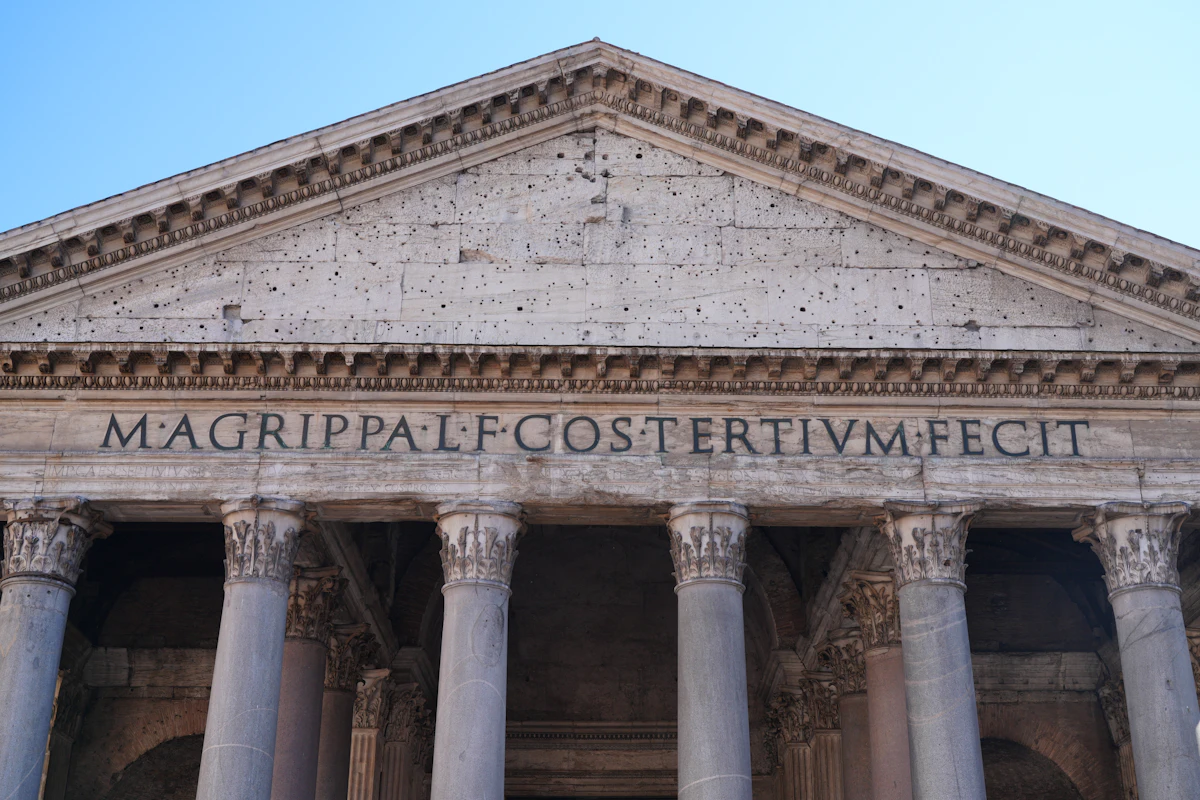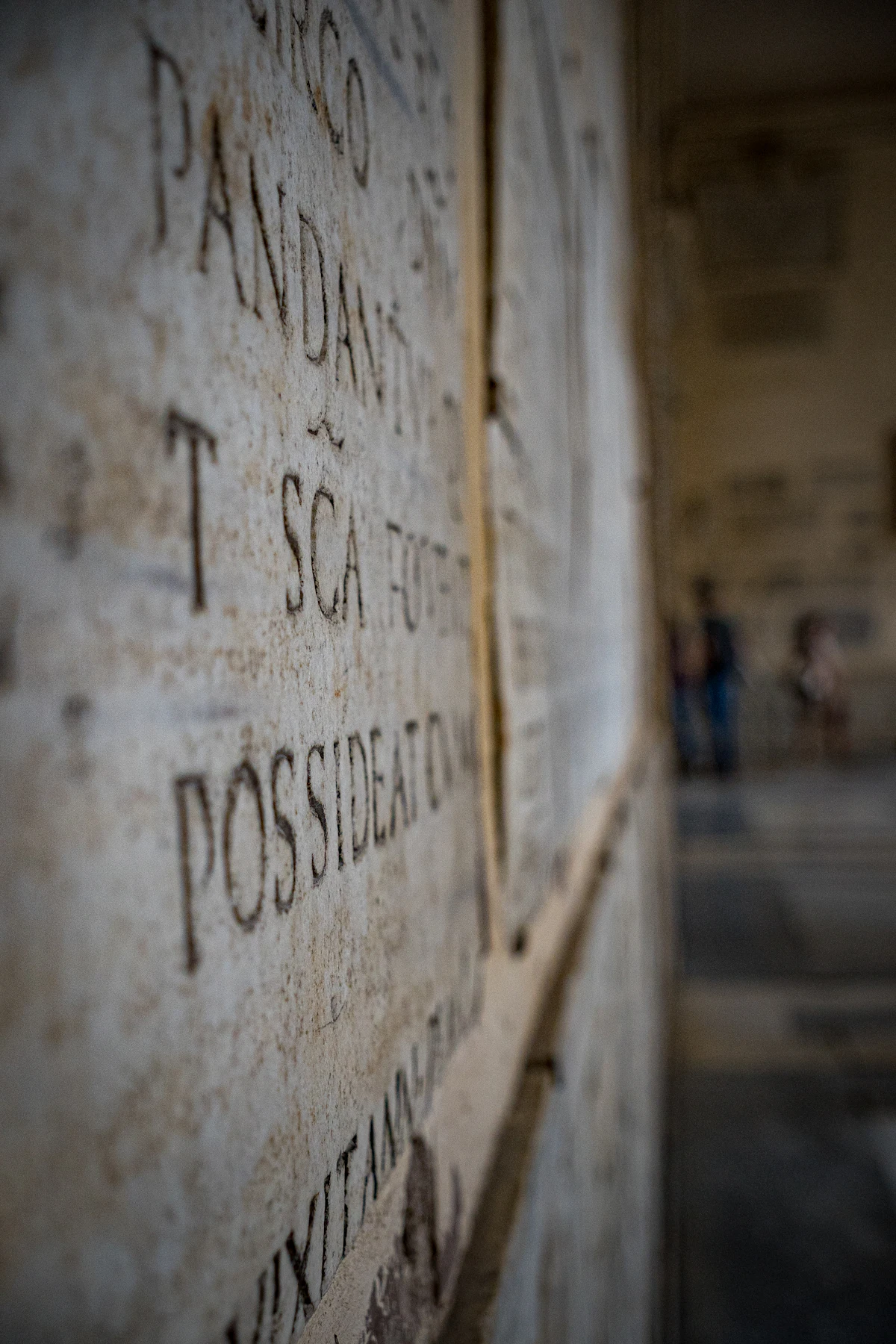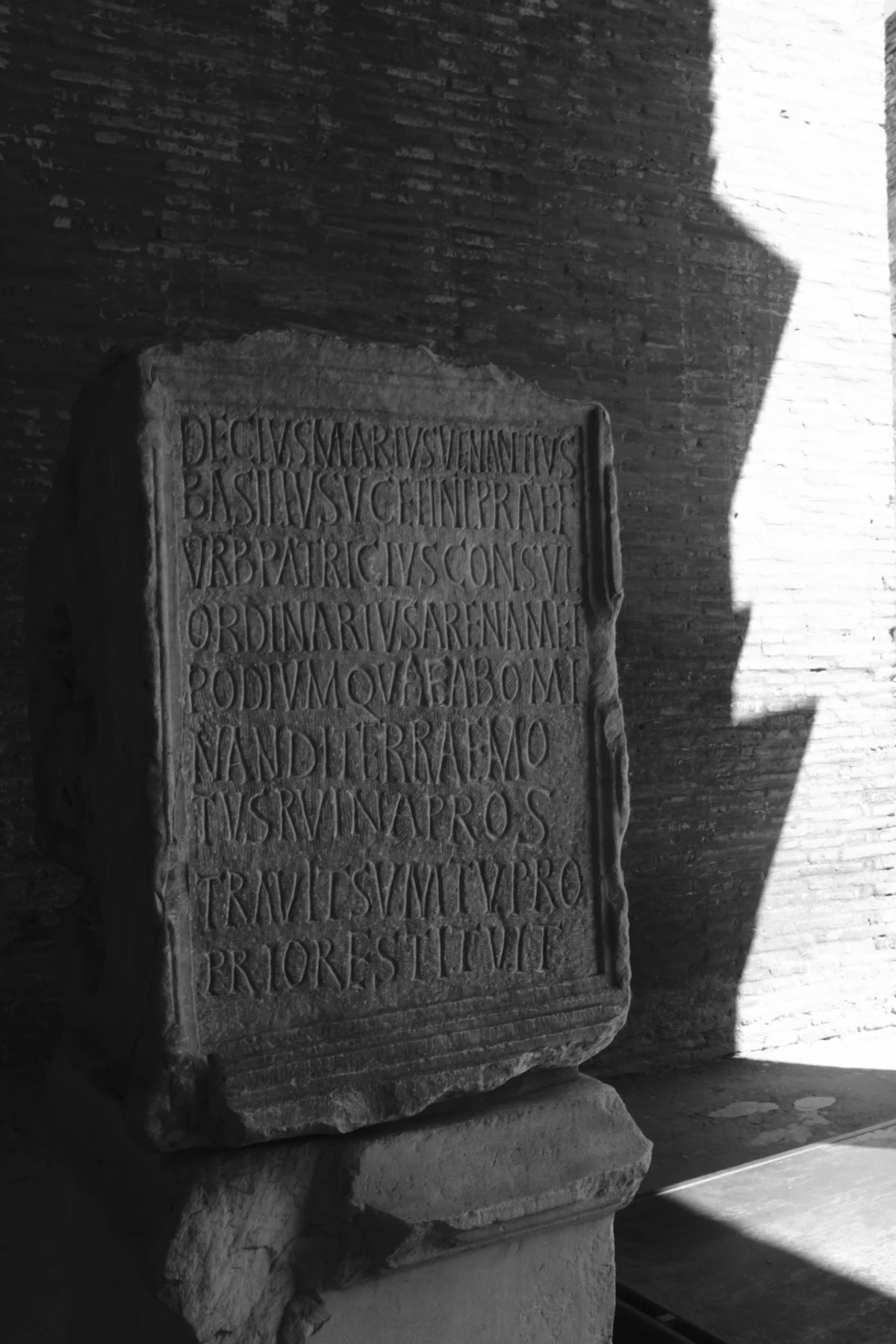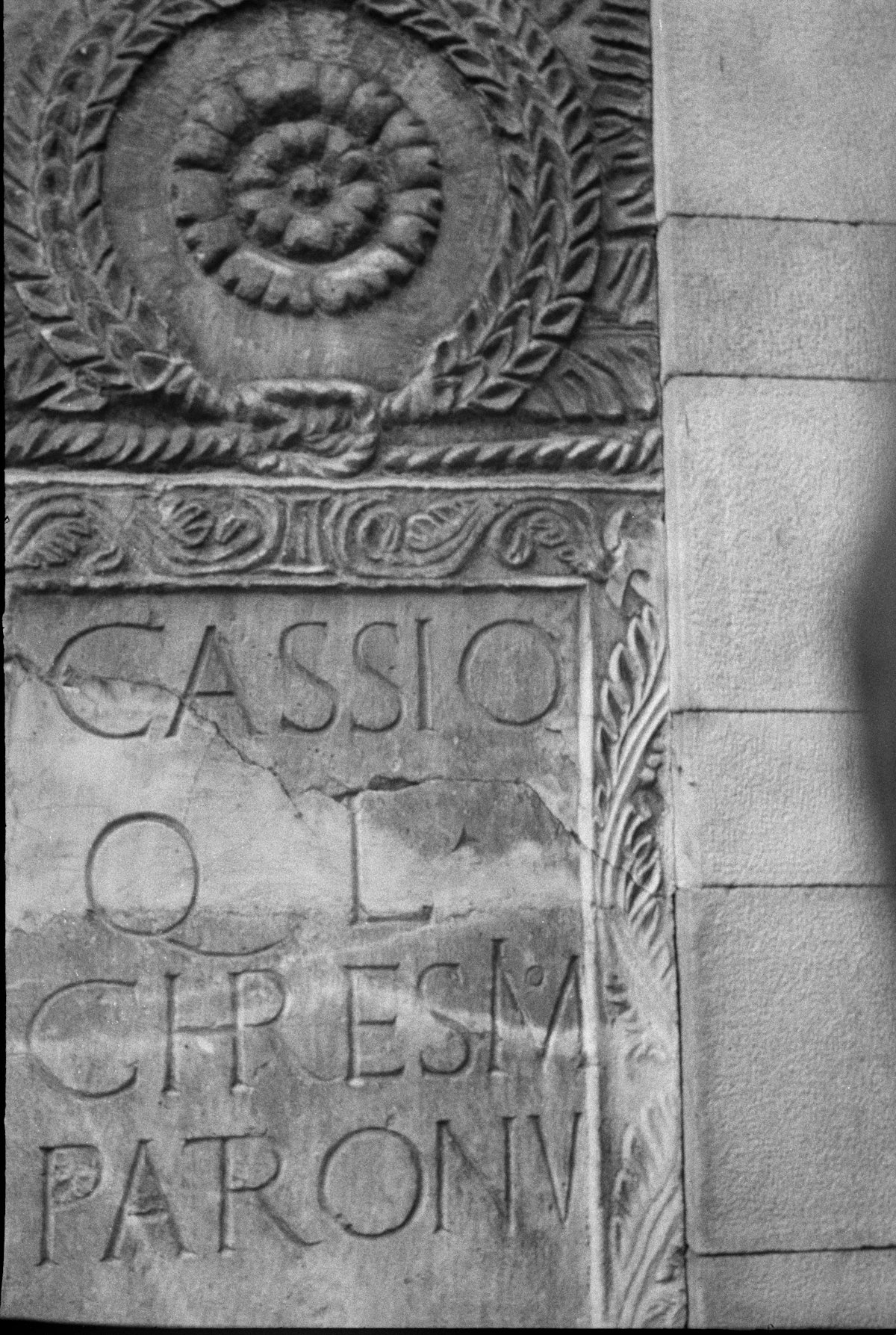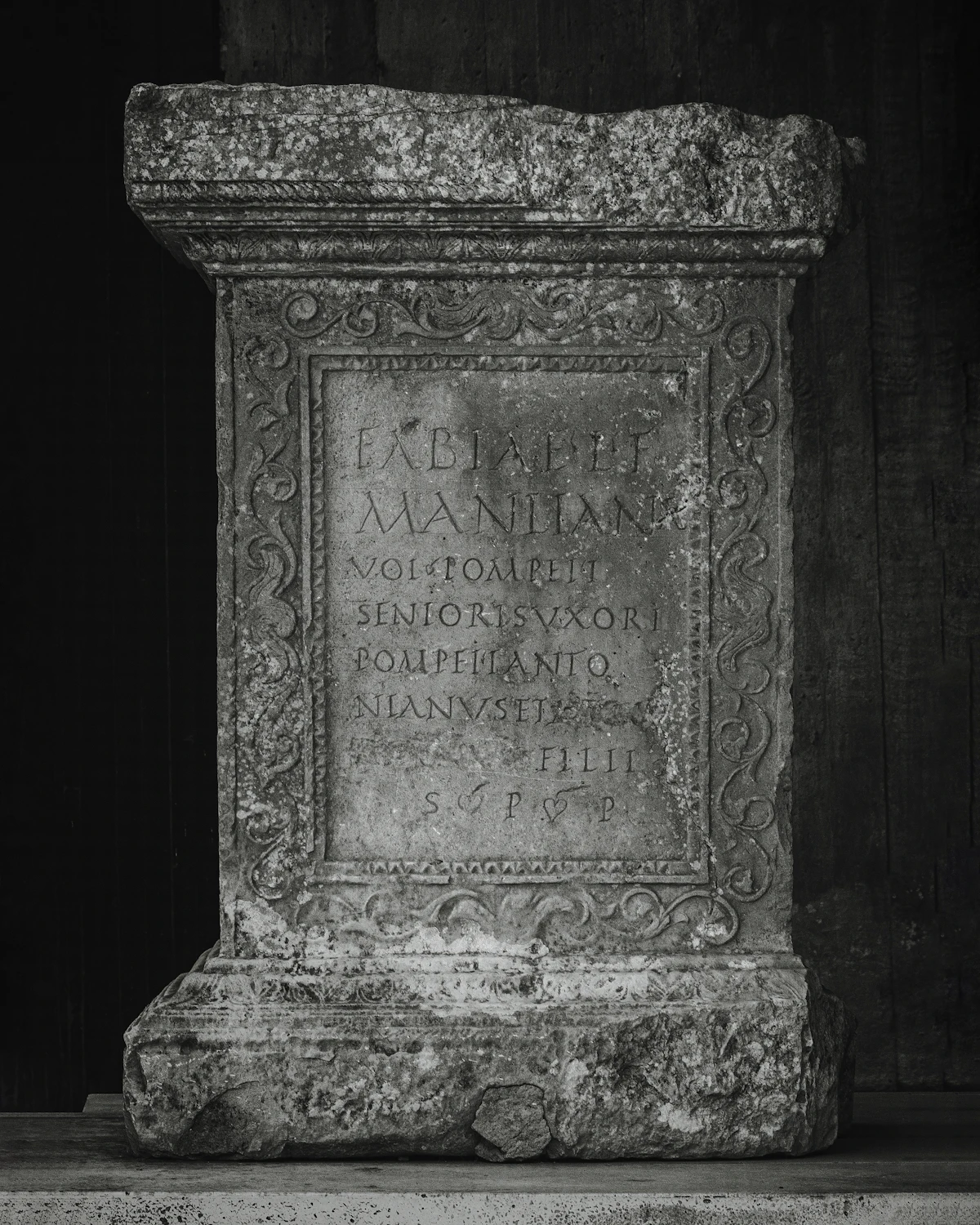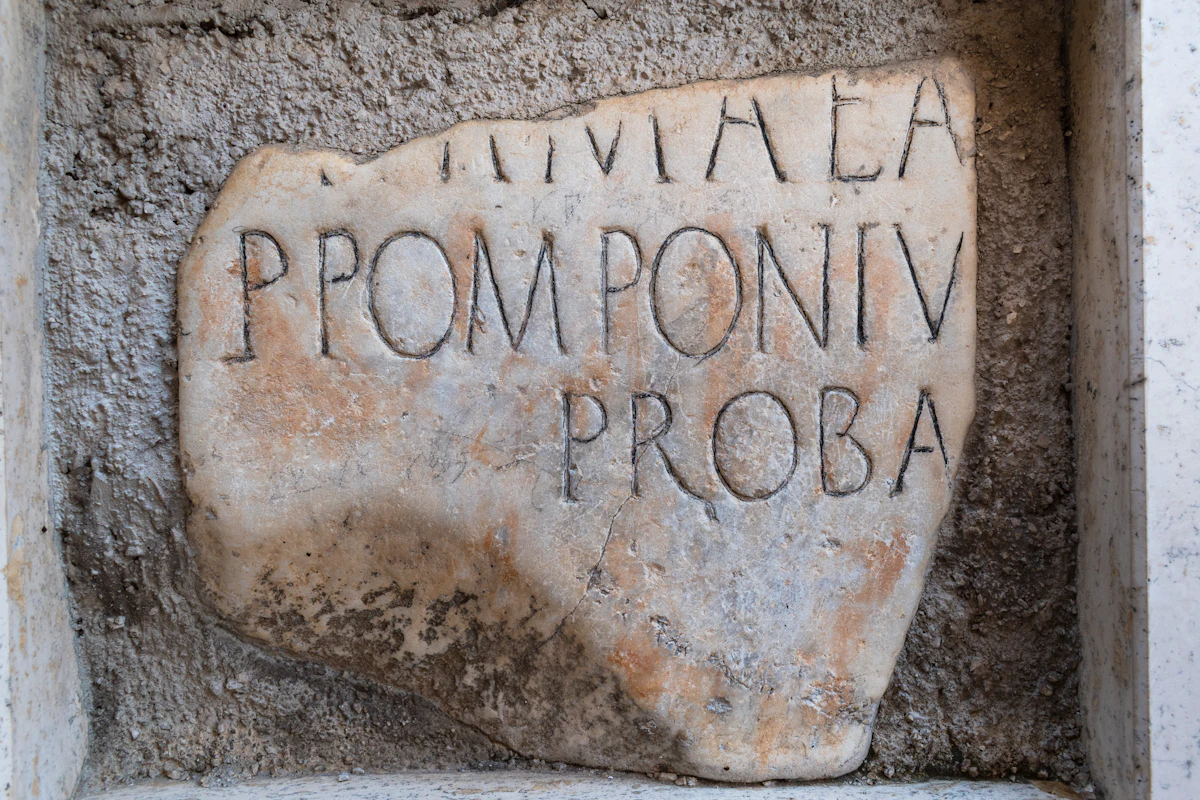
ที่ฐานของเสาหินต้นหนึ่งในกรุงโรม มีตัวอักษรชุดหนึ่งถูกสลักไว้เมื่อเกือบสองพันปีก่อน ตัวอักษรพวกนั้นไม่มีสระ ไม่มีช่องไฟที่สม่ำเสมอแบบเครื่องพิมพ์ แต่สัดส่วนของมันแม่นยำจนคนรุ่นหลังยกให้เป็นจุดสูงสุดของตัวพิมพ์ใหญ่แบบโรมัน และหลายศตวรรษต่อมา มันกลายมาเป็นฟอนต์ Trajan ที่เราเห็นบนโปสเตอร์หนังแทบทุกเรื่อง
จารึกต้นแบบอยู่บนฐานเสา Trajan สร้างขึ้นราวปี ค.ศ. 113 เพื่อฉลองชัยของจักรพรรดิทราจัน ช่างในยุคนั้นไม่ได้เขียนตัวอักษรลงบนหินตรง ๆ แต่เชื่อกันว่าใช้พู่กันแบนร่างเส้นก่อน แล้วจึงสกัดตาม นี่คือเหตุผลที่ตัวอักษรมีน้ำหนักเส้นหนาบางไม่เท่ากัน และมีเชิงเล็ก ๆ ที่ปลายเส้น ซึ่งภายหลังถูกเรียกว่า serif
คนที่ทำให้เรื่องนี้กระจ่างคือบาทหลวงชื่อ Edward Catich เขาเป็นทั้งนักบวชและช่างป้าย ใช้เวลาทั้งชีวิตศึกษาจารึกโรมัน แล้วเสนอในหนังสือ The Origin of the Serif ว่า เชิงของตัวอักษรไม่ได้เกิดจากการสกัดหิน แต่เกิดจากจังหวะของพู่กันที่สะบัดปลายก่อนยกขึ้น ข้อเสนอนี้เปลี่ยนวิธีที่คนออกแบบตัวอักษรมองรากของ serif ไปเลย
ตัวอักษรที่เรารู้จักในชื่อ Trajan วันนี้ ถูกทำขึ้นในปี 1989 โดย Carol Twombly นักออกแบบตัวอักษรของ Adobe เธอถอดสัดส่วนจากจารึกโบราณมาเป็นฟอนต์ดิจิทัล คงความสง่าของตัวพิมพ์ใหญ่ไว้ทั้งชุด และเลือกที่จะไม่มีตัวพิมพ์เล็กเลย เพราะต้นแบบโรมันก็ไม่มี นี่ทำให้ Trajan มีเพียงตัวใหญ่ ซึ่งกลายเป็นทั้งข้อจำกัดและเอกลักษณ์
สิ่งที่น่าสังเกตคือ ทำไมตัวอักษรที่ถอดจากหินอายุสองพันปี ถึงเข้ากับโปสเตอร์หนังฮอลลีวูดได้พอดี คำตอบอยู่ที่น้ำเสียงของมัน Trajan ให้ความรู้สึกเก่าแก่ ขึงขัง และน่าเชื่อถือ โดยไม่ต้องพยายาม พอวางคำว่าชื่อเรื่องหนังดราม่าหรือหนังอิงประวัติศาสตร์ลงไป มันก็ให้ความรู้สึกว่าเรื่องนี้สำคัญและจริงจังทันที
ต่างจากฟอนต์เรขาคณิตที่เกิดจากอุดมคติสมัยใหม่อย่าง Futura ที่ออกแบบขึ้นในศตวรรษที่ยี่สิบ Trajan ไม่ได้ถูกวาดขึ้นเพื่อดูล้ำสมัย แต่มันหยิบยืมความน่าเชื่อถือจากเวลา ตัวอักษรที่คนสลักไว้เพื่อให้อยู่ค้ำฟ้า พอถูกนำมาใช้ในงานร่วมสมัย มันจึงพกความรู้สึกของความถาวรติดตัวมาด้วย
เพราะให้ความรู้สึกแบบนั้น Trajan จึงถูกใช้จนล้นในงานที่อยากดูมีระดับ ปกหนังสือ ป้ายสำนักงานกฎหมาย ฉลากไวน์ ไปจนถึงตราของสถาบัน จนบางครั้งกลายเป็นทางลัดของคำว่าหรูหราและคลาสสิก การใช้มากเกินไปนี้เองที่ทำให้นักออกแบบบางคนเริ่มระวัง เพราะเมื่อทุกอย่างดูสง่าเหมือนกันหมด ความสง่าก็เริ่มจืด
จักรวรรดิที่สั่งให้สลักตัวอักษรพวกนั้นล่มสลายไปนานแล้ว แต่รูปทรงของตัวอักษรยังอยู่ และเดินทางต่อในที่ที่ช่างโรมันคงไม่เคยจินตนาการถึง บางที สิ่งที่คนเราสร้างให้ดีจริง อาจไม่ได้อยู่ยาวเพราะเนื้อวัสดุ แต่เพราะสัดส่วนของมันยังพูดกับสายตาคนได้อยู่